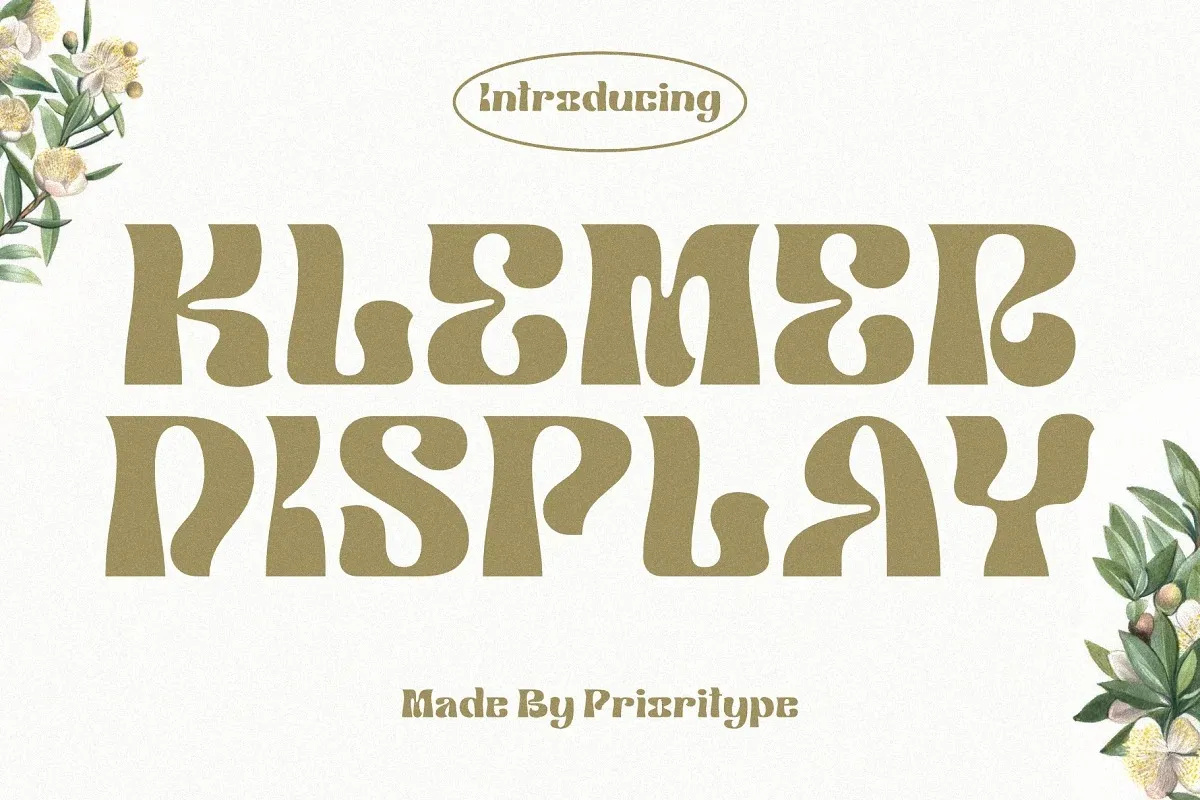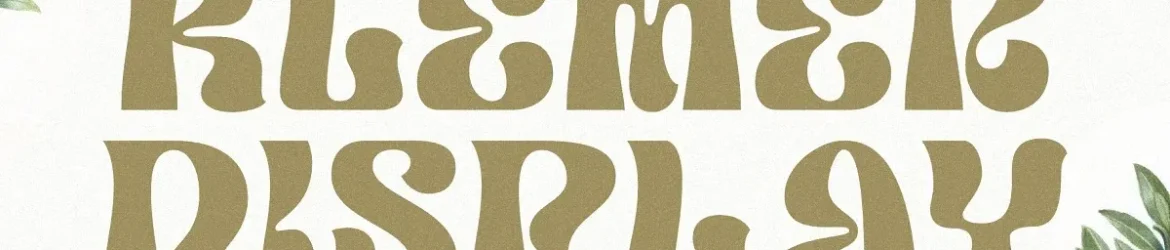
Klemer Font – Download Grátis
A Klemer Font é uma elegante seleção para projetos que exibem modernidade e sofisticação. Inspirada nos efeitos psicodélicos, mas simplificada ainda mais, esta tipografia se destaca perfeitamente tanto para design de materiais publicitários quanto para logotipos e camisas personalizadas. Seus traços finos e fluidos criam um contraste sofisticado que torna a Klemer Font uma opção ideal para designers cujos projetos buscam capturar o melhor do universo vintage moderno, sem abrir mão da contemporaneidade exigida em nossas sociedades urbanizadas. Seja para um design de outdoors chamativo ou um trabalho de marca inovador, a Klemer é uma excelente escolha para quem busca tanto originalidade quanto harmonia nas suas criações visuais.